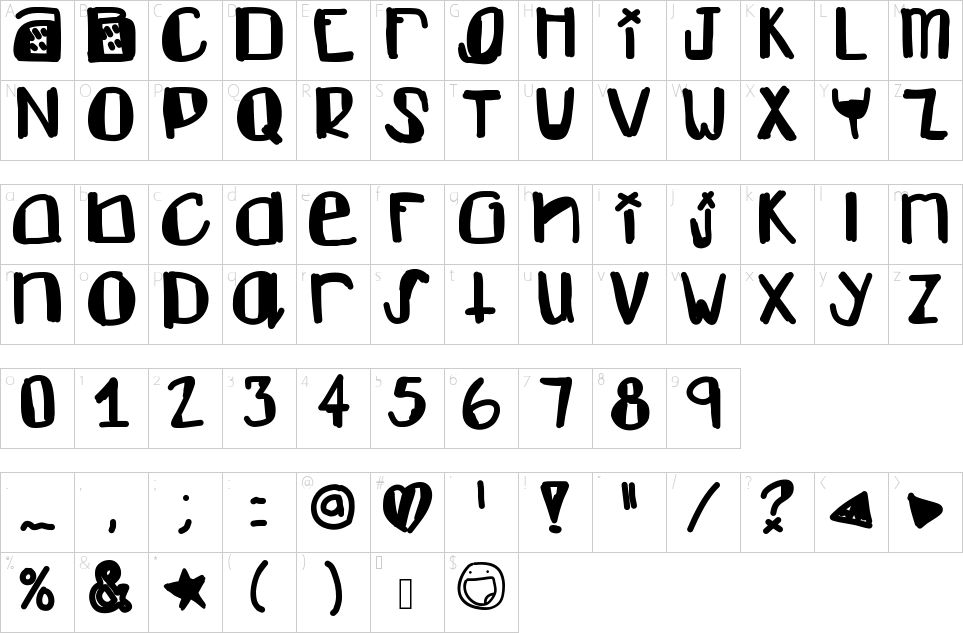
Descubra a nova fonte gratuita ‘Dont Like Font’ disponível para Windows e Mac. Desenvolvida pelo designer desconhecido Des Gomez, esta elegante fonte tem sido baixada 2.057 vezes. Se você está procurando por uma alternativa fresca e divertida à maioria das outras fuentes existentes, ‘Dont Like Font’ pode ser justamente a opção que você estava buscando. Com um design único e atraente, esta fonte pode trazer uma novidade animada para seu próximo projeto gráfico. Seja um logotipo, uma assinatura ou até mesmo um texto simples, ‘Dont Like Font’ certamente adicionará um toque especial à sua obra. Baixe agora e comece a explorar as possibilidades desta fonte divertida e versátil.